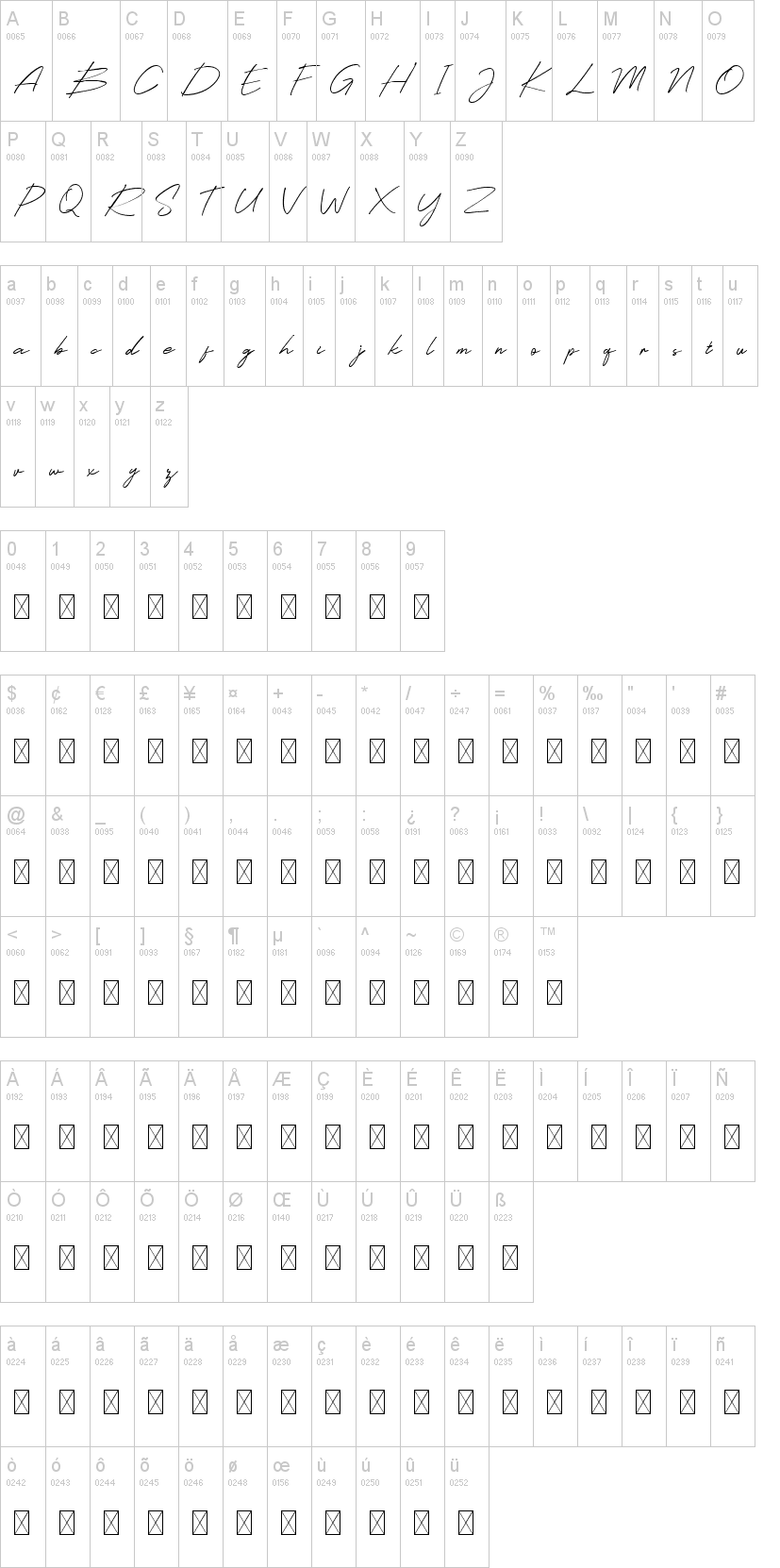
Celine Peach Script
Celine Peach Script 是一种优雅、手写的字体风格,由字体设计师 Maroon Baboon 开发。该字体的主要特征是流畅、柔和的笔画,具有优美的曲线和配合良好的字距。它的设计灵感来源于草书和签名风格,让文字看起来更加亲切和自然。Celine Peach Script 字体可用于各种设计项目,例如包装设计、商标设计、海报设计、婚礼设计和印刷品设计等。
Celine Peach Script是一款非常不错的手写艺术字体,具有很好的视觉感,适合于文化类的宣传设计、商业类品牌的广告和产品包装设计以及个性化文字排版等较多场景。
Celine Peach Script字符映射图